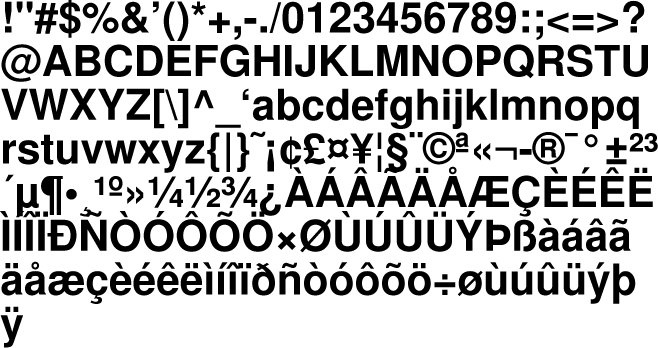
Бесплатная замена платному Helvetica Neue
Подбирал бесплатную замену платному Helvetica Neue. До финала дошли:
- TeX Gyre Heros
- Arimo
- Liberation Sans
- Lato
- Roboto
Победителем вышел TeX Gyre Heros, т.к. он очень похож на Helvetica Neue, поддерживает кириллицу и дополнительно у него есть 4 condenced начертания.
Слева Helvetica Neue, справа TeX Gyre HerosСравнение шрифтов
Если всё же нужно купить Helvetica Neue для веба, обратите внимание на Adobe Typekit. У них дешевле.
Представитель Monotype подтвердил ТАСС, что компания прекращает работу с российскими компаниями из-за санкций, введенных в связи с ситуацией на Украине.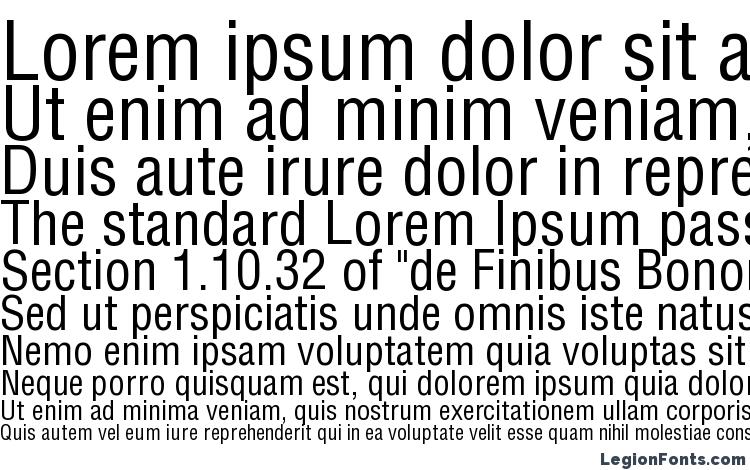
«К сожалению, учитывая нынешние обстоятельства санкций и международные отношения с Россией, мы в настоящее время не можем вести какие-либо деловые отношения с российскими компаниями или их дочерними компаниями. Мы будем продолжать следить за ситуацией и соответствующим образом обновлять нашу политику», — сообщили ТАСС в Monotype.
Редактировать:
найти Helvetica возвращает:
/usr/lib/libreoffice/share/psprint/fontmetric/Helvetica-Bold.afm /usr/lib/libreoffice/share/psprint/fontmetric/Helvetica-BoldOblique.afm /usr/lib/libreoffice/share/psprint/fontmetric/Helvetica-Oblique.afm /usr/lib/libreoffice/share/psprint/fontmetric/Helvetica.afm /usr/share/fonts/downloaded_unknown_copyright_use/Helvetica.ttf /usr/share/fonts/type1/mathematica/Helvetica-Bold.afm /usr/share/fonts/type1/mathematica/Helvetica-BoldOblique.afm /usr/share/fonts/type1/mathematica/Helvetica-Oblique.afm /usr/share/fonts/type1/mathematica/Helvetica.